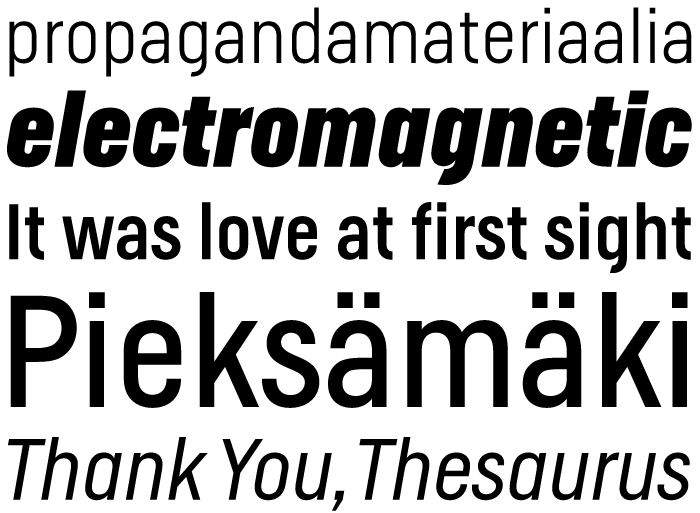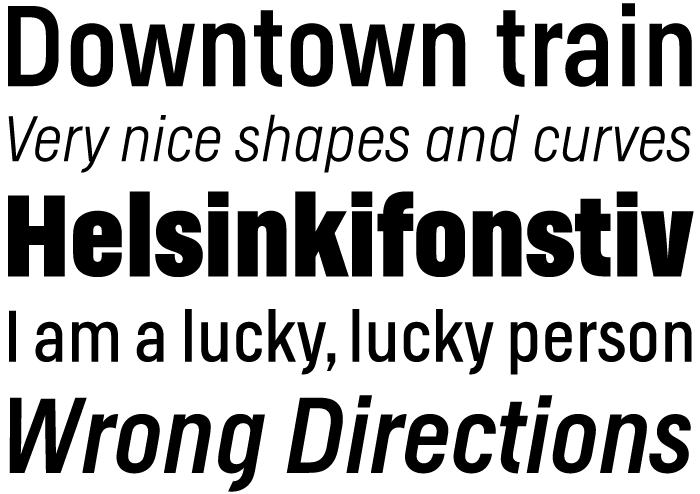
Ich habe meine Schriftfamilie Helsinki neu überarbeitet. Alle Zeichen wurden neu gezeichnet, der Zeichensatz erheblich erweitert, und kursive Schriftschnitte hinzugefügt. Helsinki ist inspiriert von der finnischen Verkehrsschilder­schrift. Sie basiert auf geometrische Formen, was ihr einen technischen Ausdruck verleiht. Helsinki ist relativ schmal und eignet sich deshalb hervorragend für Headlines oder kurze Texte. Bis Ende August gibt es auf die gesamte Helsinki Schriftfamilie 50% Rabatt.